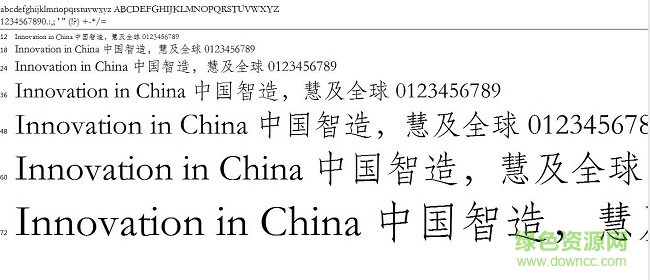
標(biāo)準(zhǔn)公文仿宋字體是一款清秀挺拔的經(jīng)典中文字體,常常用于批注、引文或是公文文件中,另外也可以用在讀物的正文排印部分,需要的朋友快來(lái)綠色資源網(wǎng)下載吧!
1.各筆劃等粗,不似宋體般的橫細(xì)直粗。
2.字體較為瘦長(zhǎng)。
3.擁有楷體的筆型,這使仿宋體較像手書(shū)體而不是宋體所屬的印刷體。